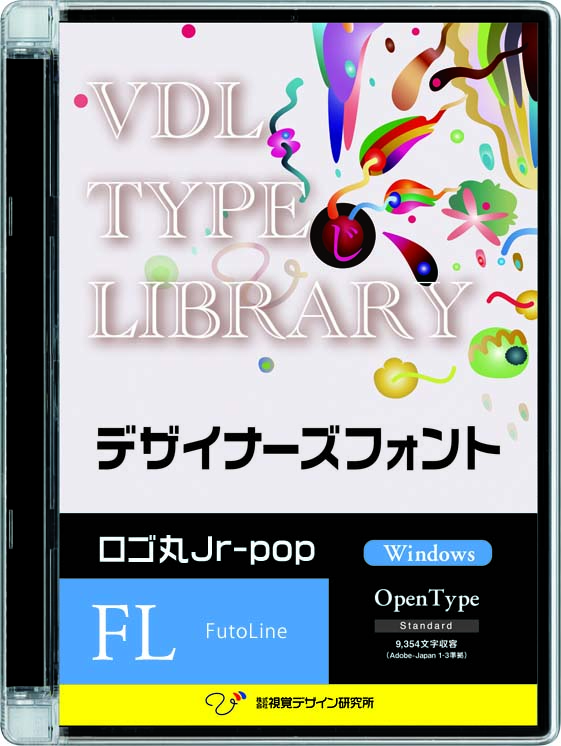
VDL TYPE LIBRARY デザイナーズフォント Windows版 Open Type ロゴ丸Jr-pop Futoline【パッケージ商品】 ※25%OFFキャンペーン価格適用
「ロゴ丸Jr-pop」は、「ロゴ丸Jr」のデザインをベースに生まれた装飾書体です。 「ロゴ丸Jr-pop-FutoLine」は、文字の輪郭線のみを強調しデザインしています。 9354文字(Adobe-japan 1-3準拠) ◆WindowsXP/WindowsVista/Windows7/Windows8/Windows10/Windows11(各日本語版)
メーカー: 視覚デザイン研究所